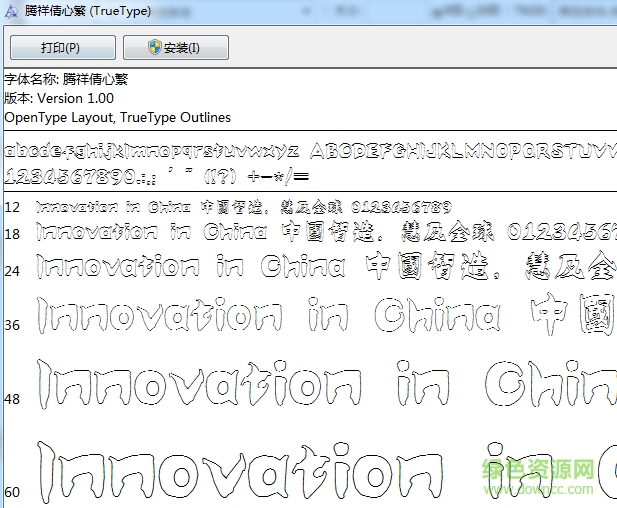
騰祥倩心繁體
騰祥倩心繁字體是超萌有趣的個性字體空心字體的寫法非常具有特色,適用于各類平面設(shè)計,對于從事廣告設(shè)計的朋友來說這款字體絕對是必備字體,有喜歡的朋友就來綠色資源網(wǎng)下載使用吧!
騰祥倩心繁字體是一款騰祥字體中的個性繁體字體,字體空心寫法別具一格,精彩的特色設(shè)計滿足多方面需要,有需要的朋友就趕快來綠色資源網(wǎng)下載吧!